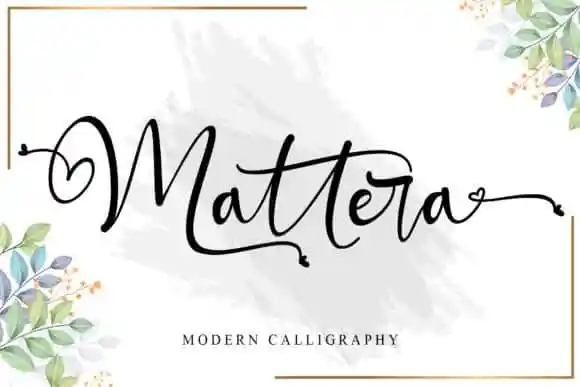
Mattera Calligraphy Font
A fonte ‘Mattera Calligraphy Font’ é uma criação cuidadosamente concebida a partir do artesanato manual que transmite os benefícios das técnicas de escrita calligráfica tradicional. Este tipo de letra apresenta um design baseado na script, mas com adaptações estratégicas para torná-la ainda mais única e encantadora. Um dos seus destaques é a sua codificação PUA, que lhe permite acessar todas as letras e desenhos chamativos facilmente. O Mattera Calligraphy Font também apresenta uma base de linha variável, linhas perfeitamente suaves, símbolos formidáveis e alternativas impressionantes, proporcionando ao designer um conjunto completo para criar designs exuberantes. Com sua versão PUA codificada, a ‘Mattera Calligraphy Font’ é ideal para aqueles que buscam uma fonte moderna e elegante capaz de enriquecer qualquer projeto gráfico. Sua simplicidade e beleza oferecem ao designer flexibilidade para explorar diversos estilos e criar designs impecáveis.